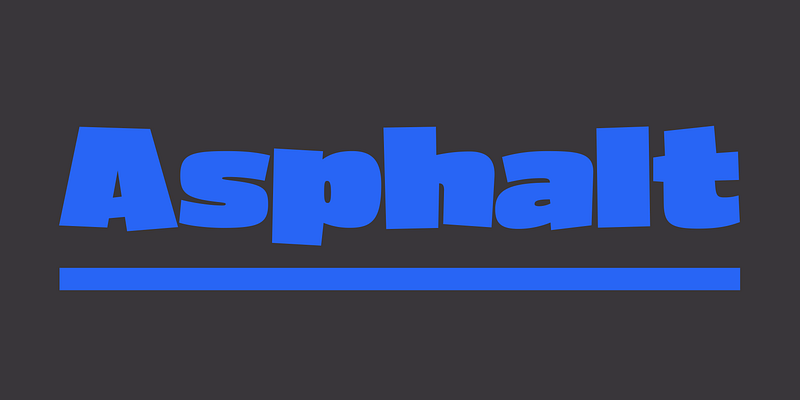
Antique Olive Nord が持つエネルギーに感心しない人はいないでしょう。このフォントに比べれば、他のウルトラボールドはすべて鈍重に見えます。Nord には Roger Excoffon の活力とガリア人のルールに対する切望が醸し出されています。Tobias Frere-Jones は、Nord のウエイト、プロポーション、リズムを彼自身がデザインした Cafeteria のカジュアルな優雅さと融合させ、ページの上でカジュアルさと踊るような活力を実現しました。彼の言葉を借りれば、Asphalt は「かすかに酩酊しているとはいえ、躍動的な回旋運動」によってスイングしています。